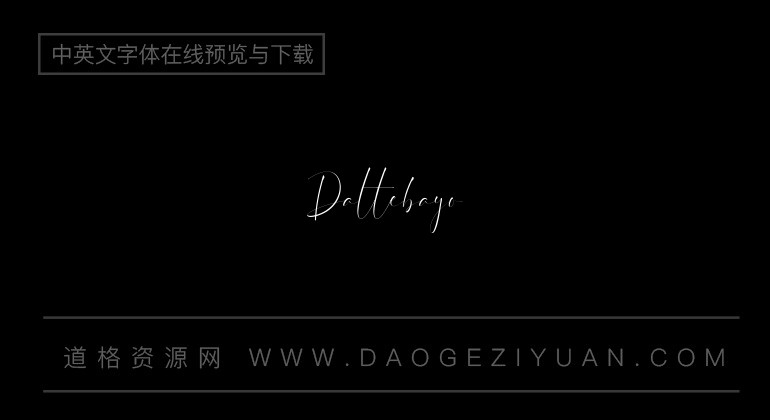
Dattebayo 字体是一种用于显示日语文本的字体。它由一位叫做“Dattebayo”的设计师开发,他的目标是创造一种能够表达日本文化的字体。Dattebayo 字体的特点是让文本看起来更加生动有趣,它具有更多的细节,比如圆润的字形,更大的字体,以及一些额外的符号,如空格,破折号,句号等等,这些符号可以帮助读者更好地理解文本。此外,Dattebayo 字体还可以用于显示其他语言的文本,比如英语,中文等等。内容介绍
Dattebayo是一款非常不错的手写艺术字体,具有很好的视觉感,适合于文化类的宣传设计、商业类品牌的广告和产品包装设计以及个性化文字排版等较多场景。